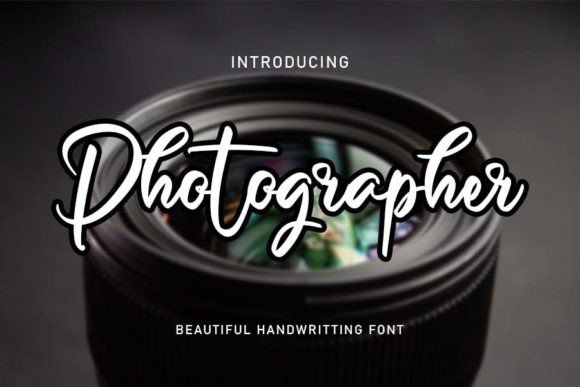
Photographer
Если вы ищете высококачественные ресурсы, такие как Photographer, этот премиум-пакет — фантастический выбор для ваших творческих проектов.
Создаете ли вы продукты POD (печать по требованию), свадебные приглашения или графику для социальных сетей, Photographer станет идеальным выбором.